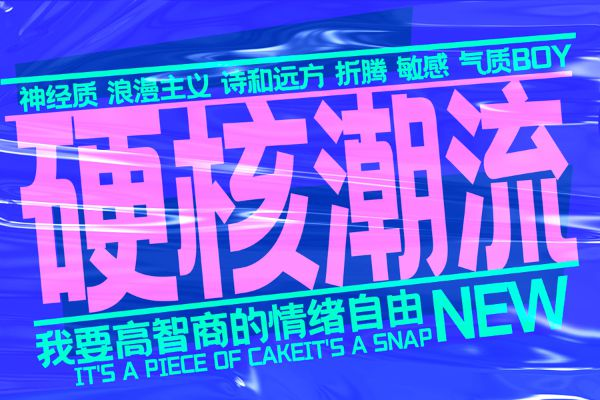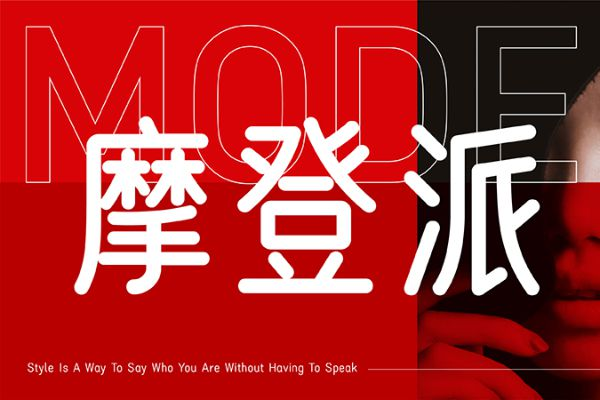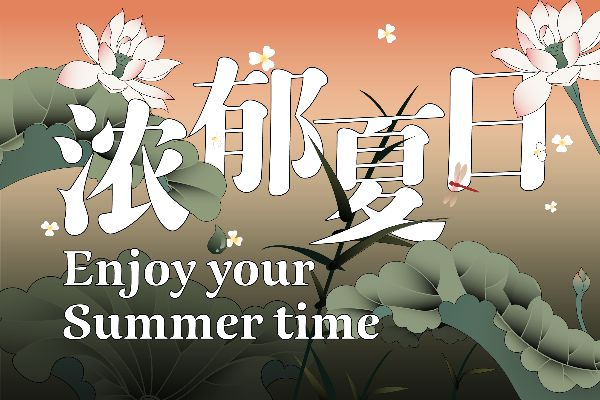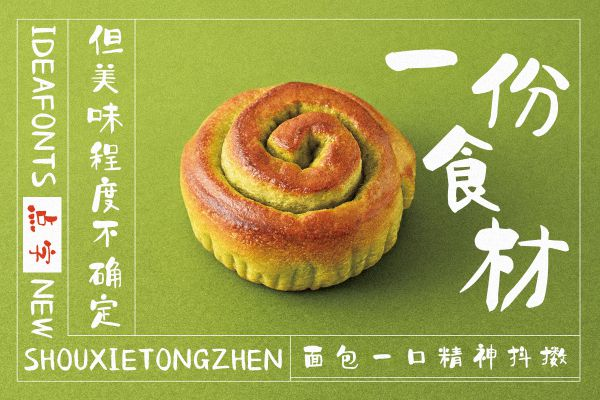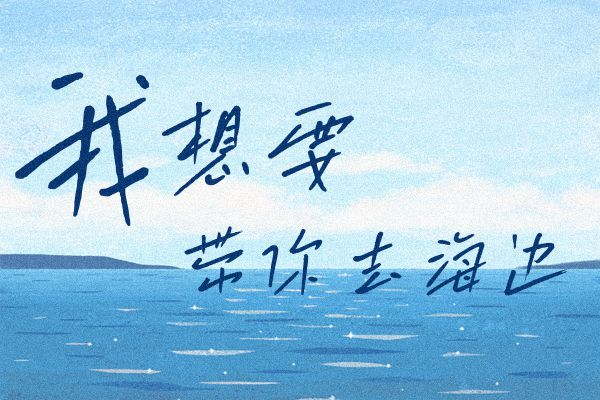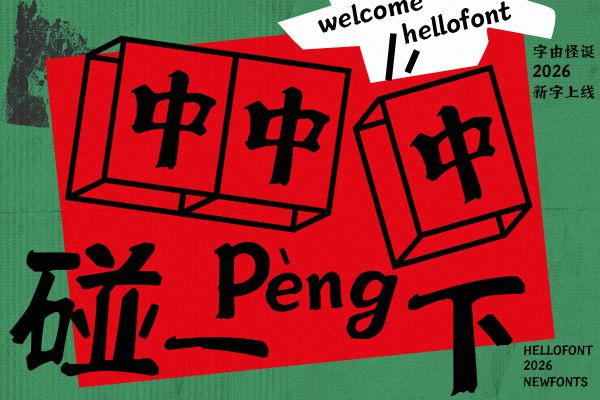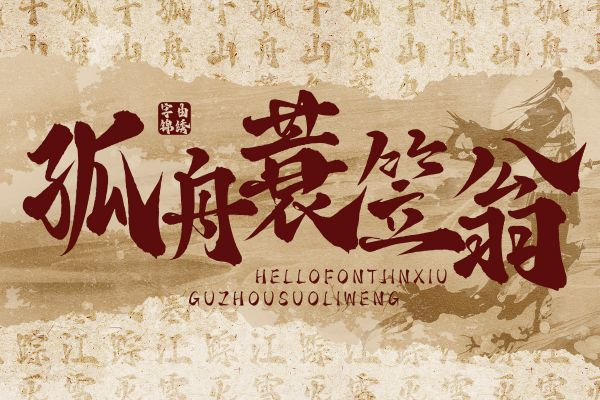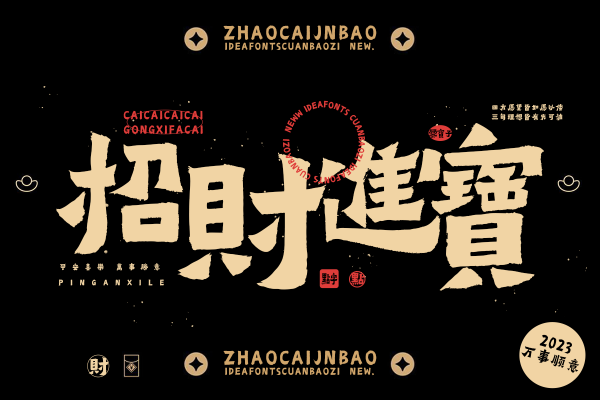
精选12款适合制作封面的字体分享
做封面这件事,包含公众号头图、小红书封面、抖音视频封面、电商主图,有一个体会越来越深:一张封面能不能让人停住划走,标题文案占三成,字体占另外三成,剩下四成才是图和配色。很多次我把图调得差不多了,换一款字体,点击率能差出一倍。
本文就给大家介绍 12 款时候制作封面的字体。
1. 优设标题黑
字由和优设联合出的爆款,笔画粗壮方正,整体带约 8° 倾斜,看着就有速度感。切角做了几何处理,没有多余装饰。我第一次用是做电商促销主图,字一放上去,画面立刻"站得住"。它只有一个超粗字重,天生就是给标题做的,不适合正文。电商 Banner、抖音封面、游戏电竞类主视觉都能用,而且永久免费商用。
1. 字由文艺黑
我公众号头图的常年主力。它在黑体的骨架里加了断开处理和柔和弧线,稳重但不死板,文艺感是悄悄渗出来的那种,不会喊"我很文艺"。做品牌标题、邀请函、文创类封面都很稳。字由自家原创,免费可商用,热度一直不低,和我一样的"懒人选法"——不知道用什么的时候先试它,多半能对。
1. 优设好身体
比优设标题黑收敛一些,方正但没那么冲,做画册内页、公众号副标题、信息类封面很耐看。它属于"不抢眼但靠谱"的那类,我常拿它做封面上的小字标签——"干货""首发""3 分钟"这种,配一个粗主标,层次就出来了。
1. 汉仪瑞云飞宋
宋体做封面其实比想象中出片,关键是挑对款。瑞云飞宋在字由里热度很高,笔画带一点飞白感,不似传统宋体那么"书卷气重到老气",配文化类、茶类、文创类封面刚好。我做了一期"老茶馆"主题的小红书封面,主标用它,评论区有人专门问字体。要注意宋体字号不能太小,缩到封面的小图尺寸容易糊。
1. 字由芳华体
温柔手写风,笔画偏细,弧度软,像用毛笔轻轻带出来的那种感觉。我做治愈系、情感类、读书类封面时用得最多。有一回做"周末独处清单"的头图,主标芳华体,配一张暖光书桌图,收藏比平时高一截。它不适合走力量感的封面,走温柔路线才是主场。
1. 江西拙楷
朴拙感很强的一款手写楷体,不是标准楷书的规整,是带点"我慢慢写、不赶"的味道。国风、非遗、文创、汉服、历史类封面都能用。我做过一期"景德镇手作"的封面,主标江西拙楷,配图是陶坯,风格咬得很紧。识别度比纯行草高,老人也能一眼认出来。
1. 点字手写童真体
粗细笔画交替,有些笔画会稍微超出边界,像小朋友写的,但又不乱。母婴、亲子、儿童绘本、游乐园、教育类 App 封面闭眼选。我有朋友做育儿号,封面主标全换成这款,留言说"看着就像懂孩子的人做的"。会员商用,字由里能直接激活。
1. 点字飒爽手写体
突破传统书写结构,笔势利落,带点"我不在意你认不认真看但我有自己的劲儿"的洒脱。我做女性向内容、职场成长类封面时用过,配深色底+大字距,效果挺惊艳。不适合太严肃的题材,走个性路线的封面才放得开。
1. 字由怪诞
苍劲粗手写,笔墨感重,视觉冲击强,排版时不用怎么调就有大气感。我做文化展览海报、主视觉标题时用过一回,主标怪诞+副标文艺黑,一粗一细一手写一现代,层次立刻出来。会员商用款,封面主标位给它不浪费。
1. 字由锦绣
中国风粗手写,设计理念是"繁花如锦",笔意豪放但结构没散。做国潮封面、传统节日封面、文创主视觉都合适。我去年做中秋封面,主标锦绣,配朱红底+金线纹样,评论区问了三次字体。它和江西拙楷的区别是:拙楷走朴,锦绣走盛。
1. 点字爨宝子
圆润可爱那一挂,线条肉肉的,没什么攻击性。母婴、萌宠、美食、甜品店封面都能用。我帮一个猫咖做过抖音封面,主标爨宝子,配猫咪探头图,店主说进店的人真有拿着手机对照封面的。会员商用,字由里搜得到。
1. 点字浅夏体
清新手写,笔画偏细,带点少女感和呼吸感。旅行 Vlog 封面、生活记录类标题、春夏主题封面很加分。我做过一期"初夏骑单车"的小红书封面,主标浅夏体,配浅绿浅黄调,点赞比平均高 40%。免费商用,字由里在"免费商用"筛选项里能翻到。
选择字体的策略
挑封面字体的时候,我自己有个小习惯:先定封面的"情绪"——是要冲(促销、发布、硬核测评),还是要柔(治愈、亲子、生活),还是要拙(国风、文创、手艺)。冲的选优设标题黑、得意黑这种粗黑派;柔的选芳华、沐瑶、浅夏;拙的选江西拙楷、字由锦绣。情绪对了,字体就对了大半。
以上 12 款是我目前封面字库里的比较常用的,黑体、宋体、手写、书法、圆体、童趣、潮流都覆盖到了,公众号、小红书、抖音、电商主图四类常见封面场景基本能对号入座。你可以先挑三四款顺手的激活留着,下次做封面就不用来回翻了。